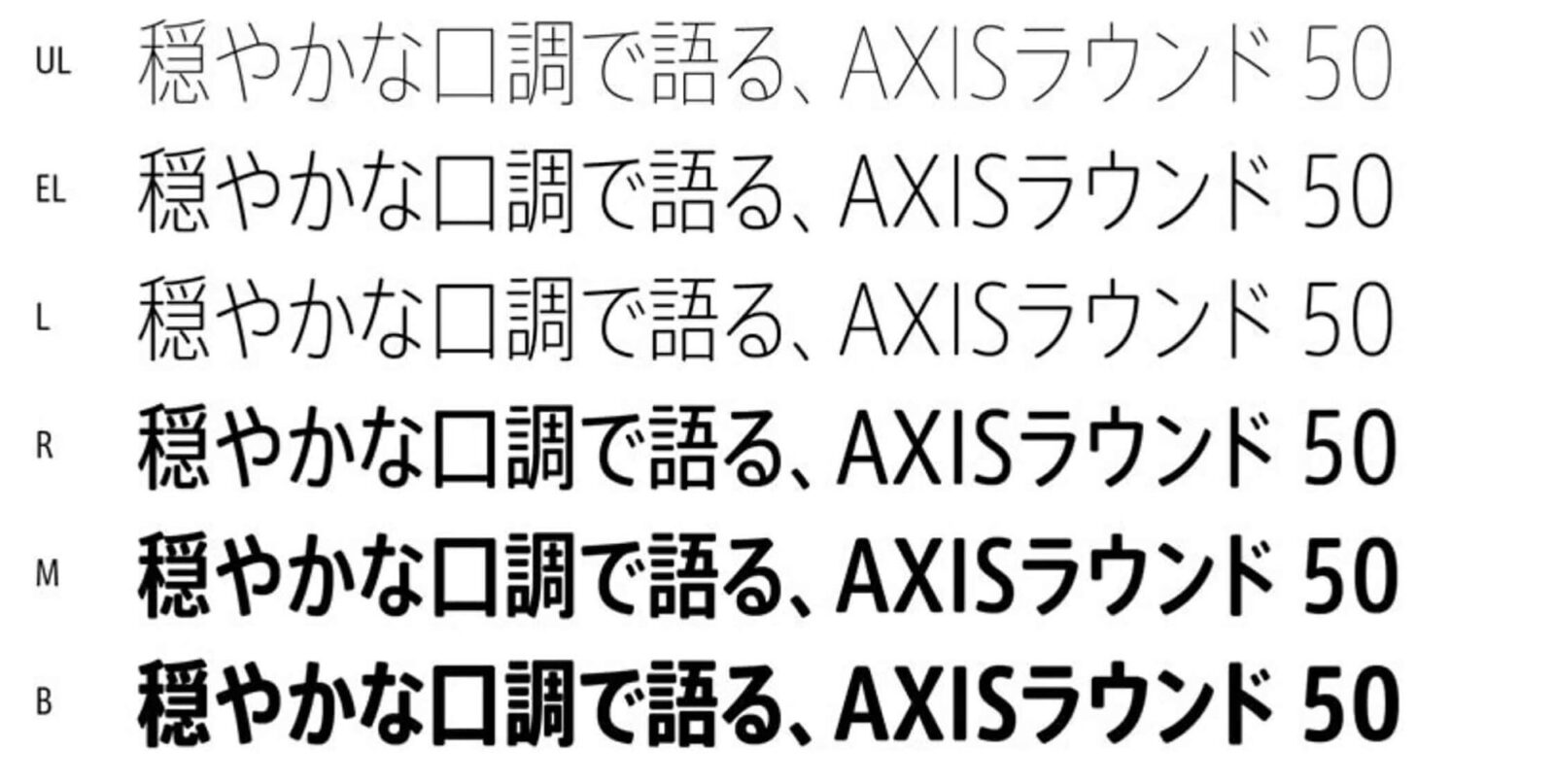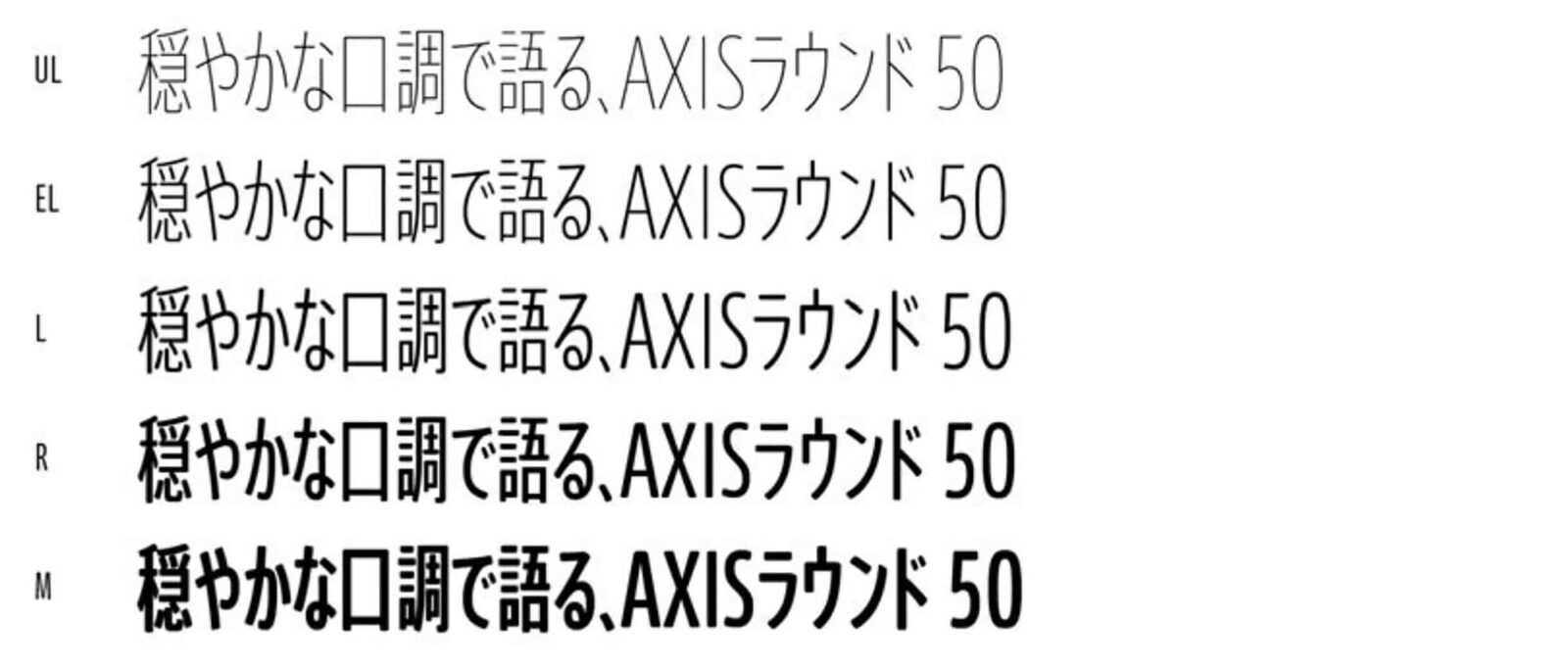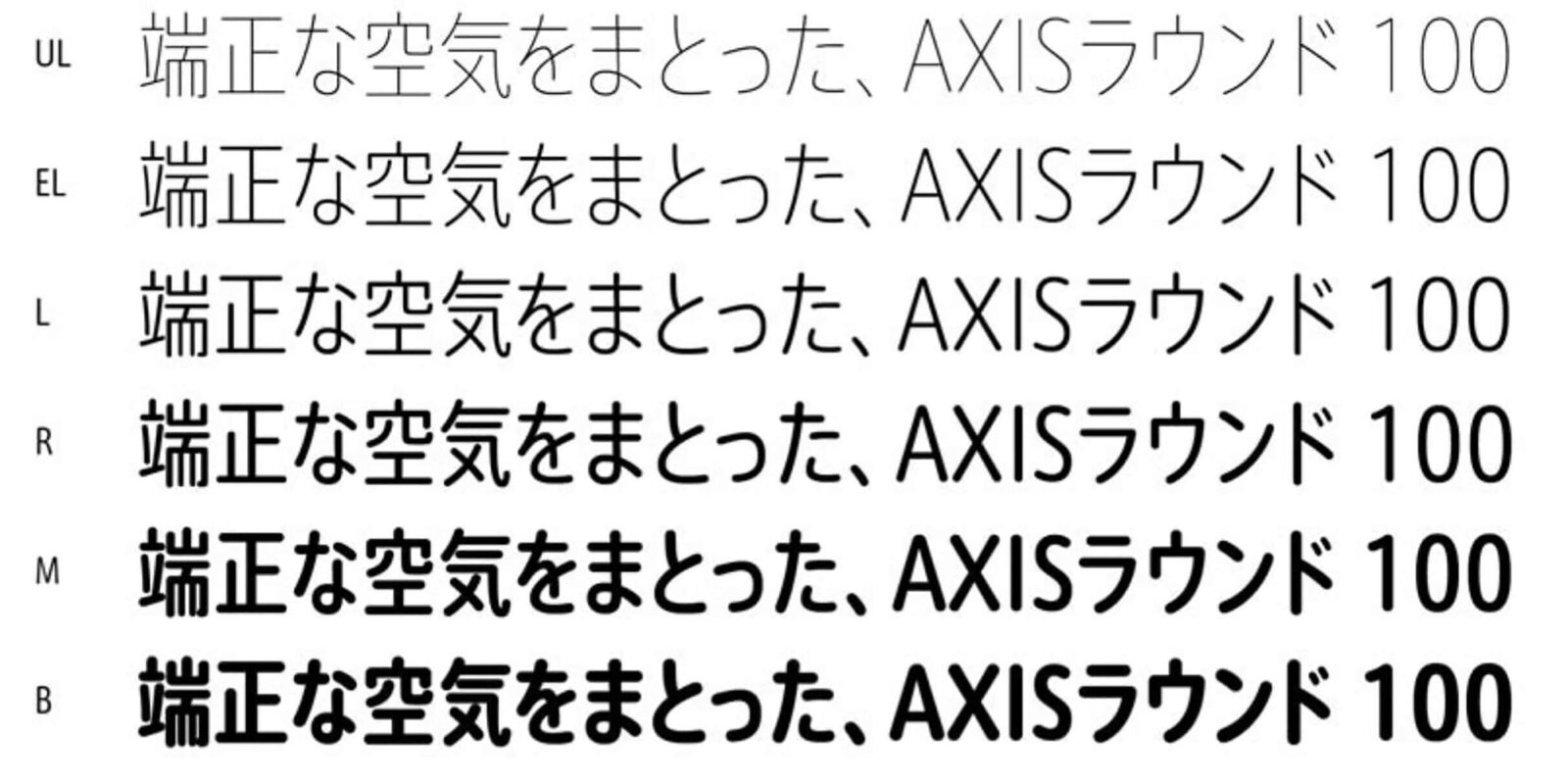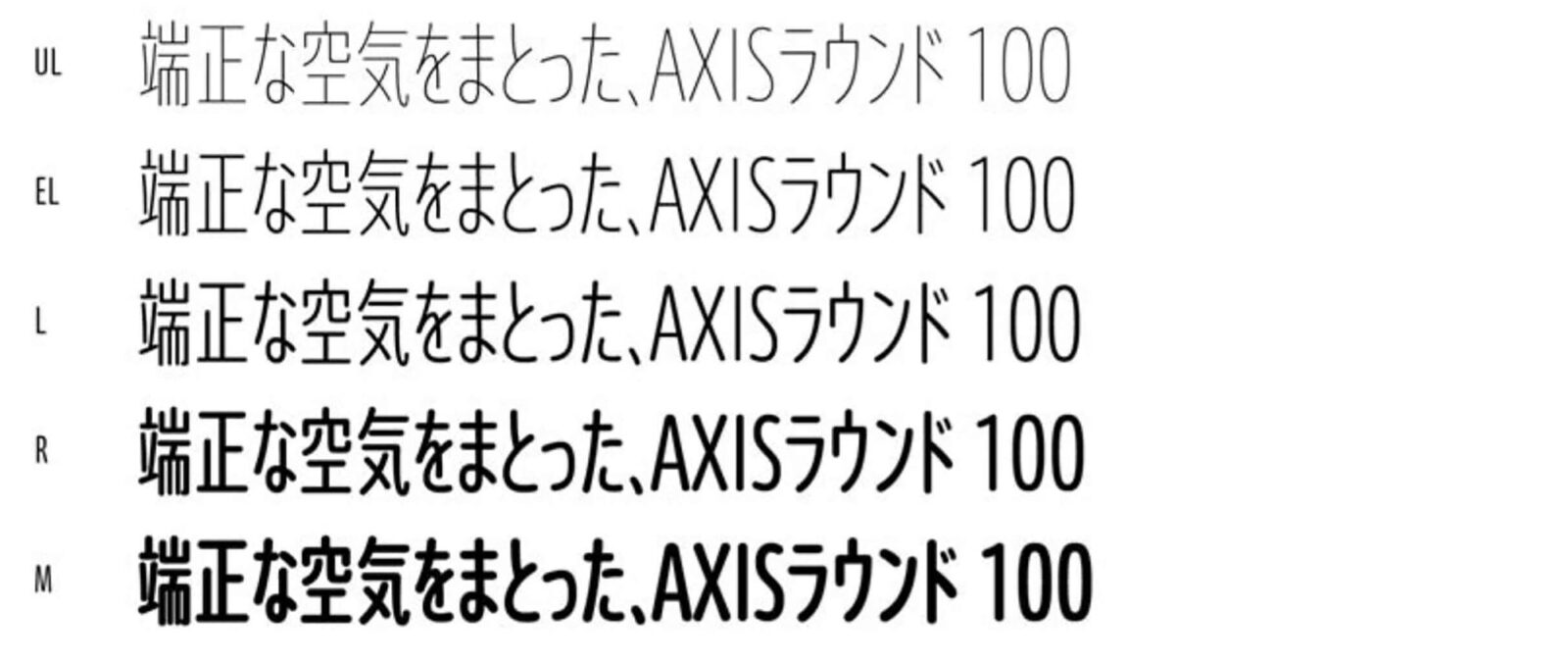
タイププロジェクト、AXIS ラウンドシリーズの コンデンス・コンプレスを発表
AXIS ラウンド 50 と AXIS ラウンド 100、それぞれ 11 フォントを同時発
タイププロジェクト株式会社 (東京都練馬区 代表取締役社長 鈴木 功、以下 タイププロジェクト) は、柔らかい空気を演出する AXIS ラウンド 50、そして見出しなどで効果を発揮する AXIS ラウンド 100 の両書体の、コンデンスとコンプレスを同時発売することを発表しました。
AXIS ラウンド シリーズのデザインは、通常の丸ゴシックとは異なり、内径を丸めていないことによりモダン・サンセリフのシャープな表情を残しています。わずかな丸みで穏やかな表情の AXIS ラウンド 50 に対し、AXIS ラウンド 100 は、ストロークの先端がほぼ半円になっています。和文長体ファミリーの先駆けとなった AXIS Font のコンデンスとコンプレス同様、長体に適した骨格で基本設計をおこなっています。
コンデンスのウエイトは、UL(ウルトラライト)、EL(エクストラライト)、L(ライト)、R(レギュラー)、 M(ミディアム)、B(ボールド)の 6 種類、コンプレスのウエイトは、UL(ウルトラライト)、EL(エクストラライト)、L(ライト)、R(レギュラー)、M(ミディアム)の 5 種類で構成しています。
タイププロジェクトの代表取締役 鈴木 功は、「AXIS ラウンドのコンデンスとコンプレスは、ニュートラルさが持ち味の AXIS Font ファミリーのなかにあってとりわけユニークな個性をもったフォントです。 AXIS Font のコンデンスとコンプレスは、空間効率の良さと可読性の高さによって、サインシステムなどで多く採用されています。AXIS ラウンドのコンデンスとコンプレスは、このような機能に加え、親しみやすさという特徴を備えていますので、活用シーンがさらに広がることを期待しています」と述べています。
AXISラウンド50 コンデンス
AXISラウンド50 コンプレス
AXISラウンド100 コンデンス
AXISラウンド100 コンプレス